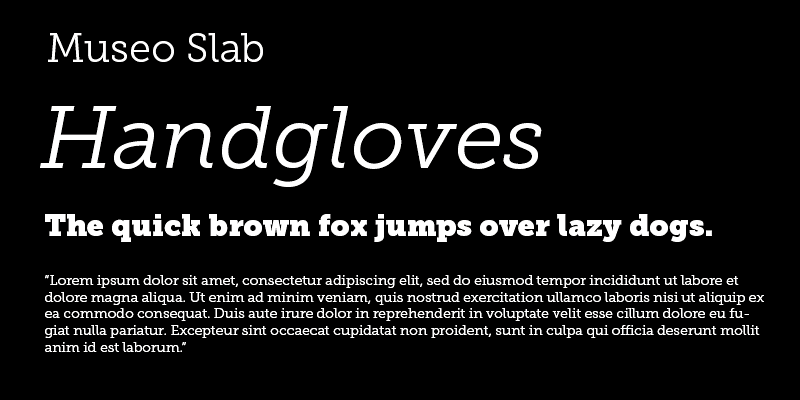
Museo Slab es la versión slab serif de la conocida familia de fuentes Museo. Es una robusta slab serif con la amabilidad de Museo. Si está buscando un toque moderno, pero desea conservar la legibilidad y la claridad, Museo Slab es un buen lugar para comenzar.
Jos Buivenga vive y trabaja en Arnhem. Comenzó a diseñar tipos de letra en 1994 y abrió su casa tipográfica exljbris diez años después. Es más conocido por su familia de tipos de letra Museo y también por la manera en que comercializa sus tipos de letra.